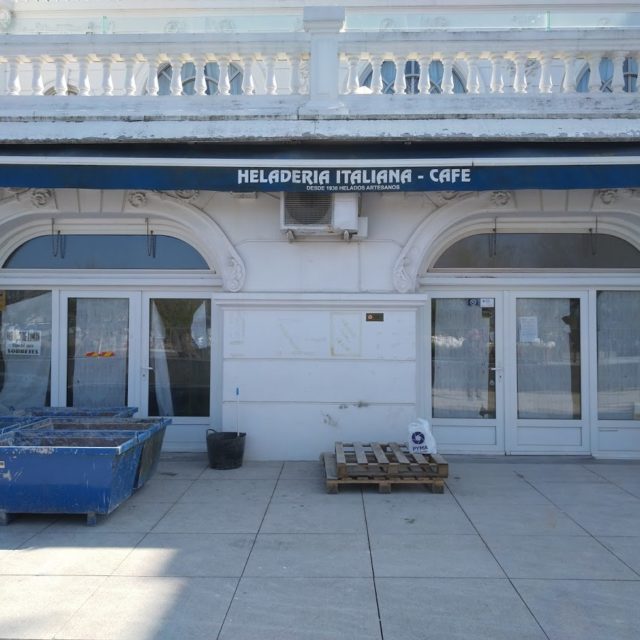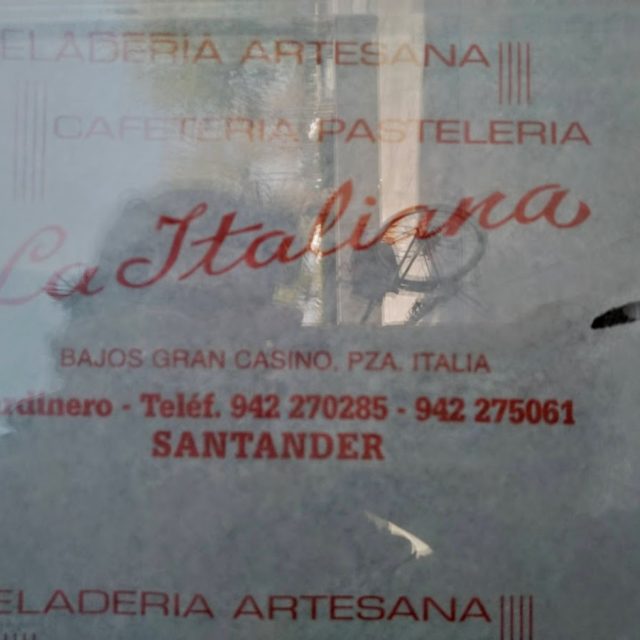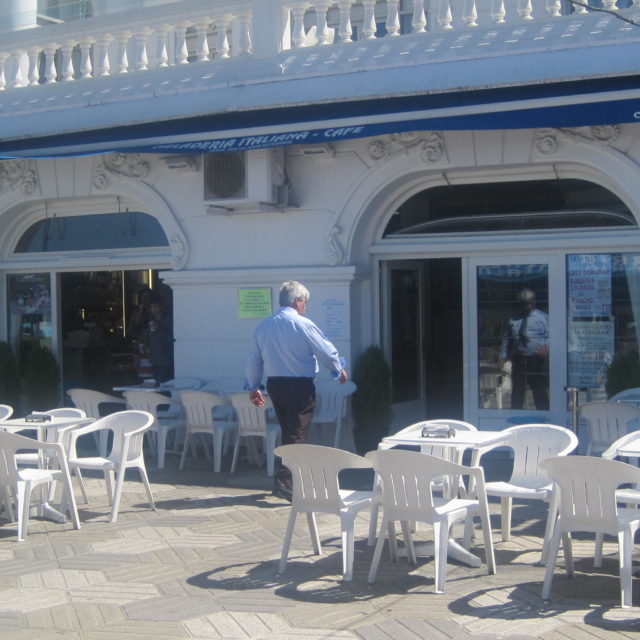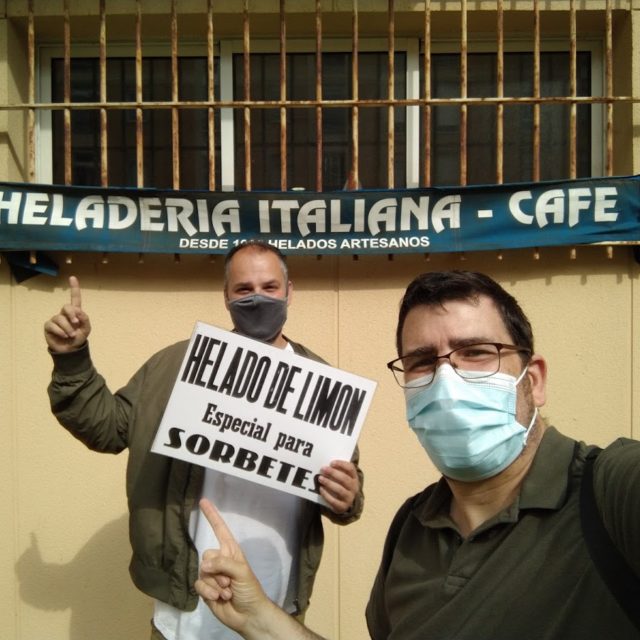
Heladería La Italiana
A finales de marzo nos enteramos del repentino cierre y desmontaje de la heladería “La Italiana” en la Plaza de Italia; Esta heladería ubicada en los bajos del Casino, de El Sardinero, ha sido siempre un referente en la zona. Abierta en 1916, llevaba desde 1938 en manos de la misma familia. Su tercera generación Raúl Rodríguez, ha sido quien ha bajado definitivamente la persiana.
Se ha podido rescatar el faldón del toldo que llevaba muchos años dando sombra a la entrada y que servía para identificar el local, y por otro lado el mítico cartel de “Helado de Limón especial para Sorbetes” en tres tipografías.
Fachada tras el cierre (los autores)
Papel de la heladería que tapaba la obra (los autores)
Fachada y terraza (2013, del blog de Pamela Cahill https://pamelacahill.com/2013/05/10/my-favourite-scoop-ice-creams/)
Distribución de los locales conocidos de la ya vieja Plaza de Italia. Ahí tenéis también el de la cafetería Lisboa, de que tenemos otro post de “recuperados” (2005, wikipedia)